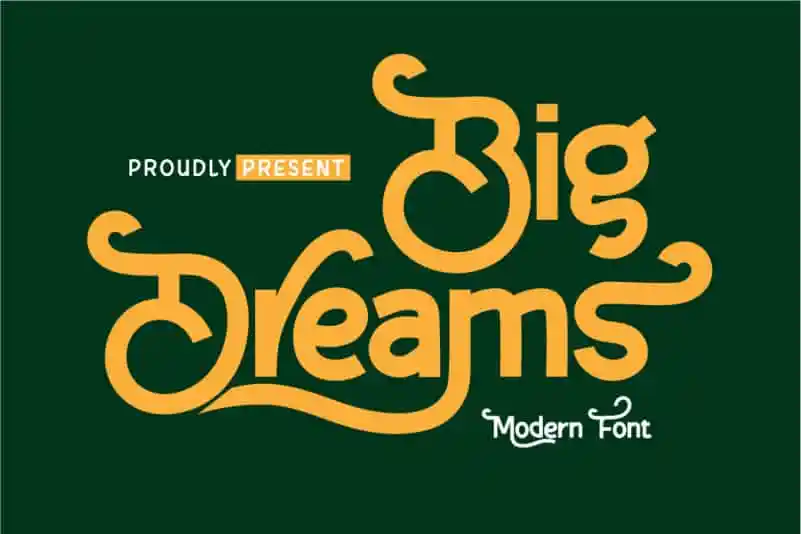
Big Dreams Display Font – Download Grátis
A fonte ‘Big Dreams Display Font’ do designer twinletter oferece uma abordagem versátil para projetos de design variados, desde invitations casamento até adesivos de promoção de bebidas e alimentos. Suavemente sofisticada, a Big Dreams Display combina com gráficos abstratos perfeitamente para criações inovadoras em diversos campos da arte visual. Esta font é particularmente ótima para projetos de convites nupais, designs com citações, identidades de negócios digitais e publicidade. O design também se destaca para anúncios, marcas comerciais e para qualquer tipo de projeto que exija um estilo handwritten real ou não. E, por último mas não menos importante, a fonte é perfeita para textos e posters.